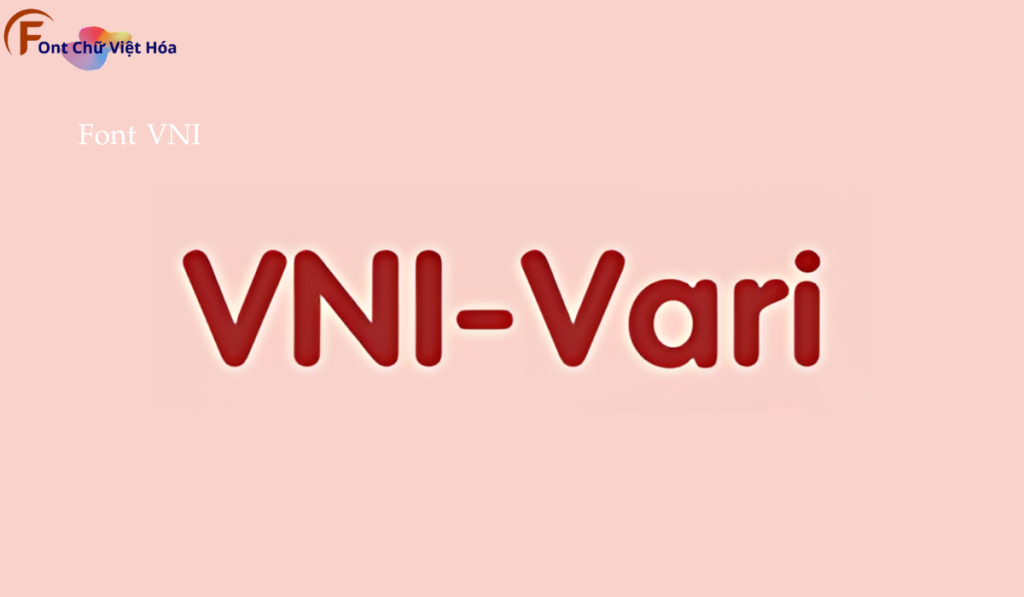
Font VNI Vari Việt Hóa
Font VNI Vari Việt Hóa, thuộc bộ font VNI, mang phong cách hiện đại và sáng tạo, phù hợp cho các dự án thiết kế như poster, logo, và bao bì sản phẩm. Với các nét chữ không chân và độ dày đều đặn, Font VNI Vari Việt Hóa không chỉ dễ đọc mà còn tạo cảm giác hiện đại và phá cách. Việc Việt hóa font giúp người dùng dễ dàng tích hợp vào các thiết kế tiếng Việt, mang lại sự tiện lợi và nâng cao tính thẩm mỹ.